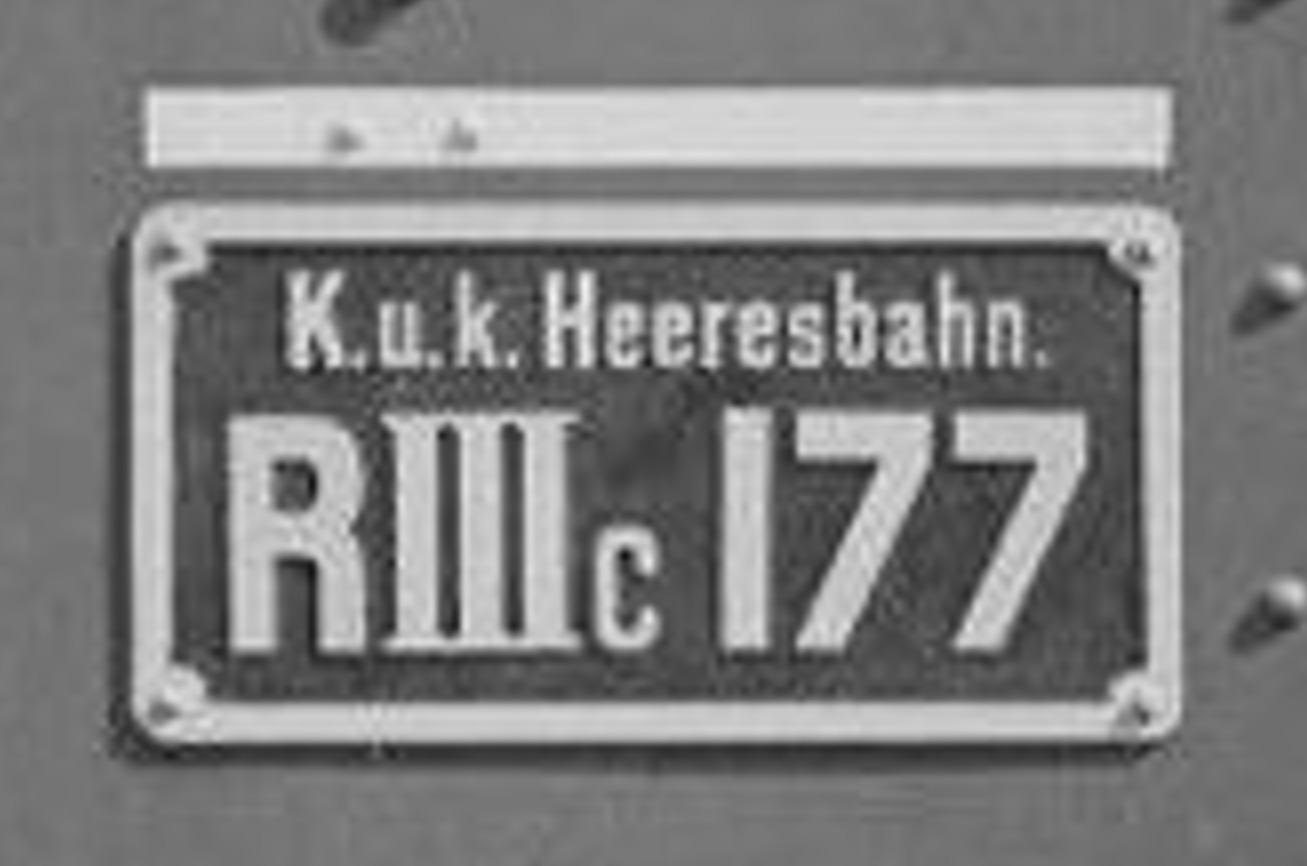
Suche Schriften auf einem Dampflok Nummernschild (1918)
Es handelt sich um einen Aussschnitt aus einer alten Fotografie. Darum ist leider keine höherer Auflösung/bessere Qualität vorhanden. Die Lok auf der das Schild war, kam in Österreich zum Einsatz. Es scheint sich um eine Schriftmischung zu handeln – die Römische Drei stich für mich heraus.
Es wäre super, wenn mir jemand helfen könnte die Schriften zu identifizieren.